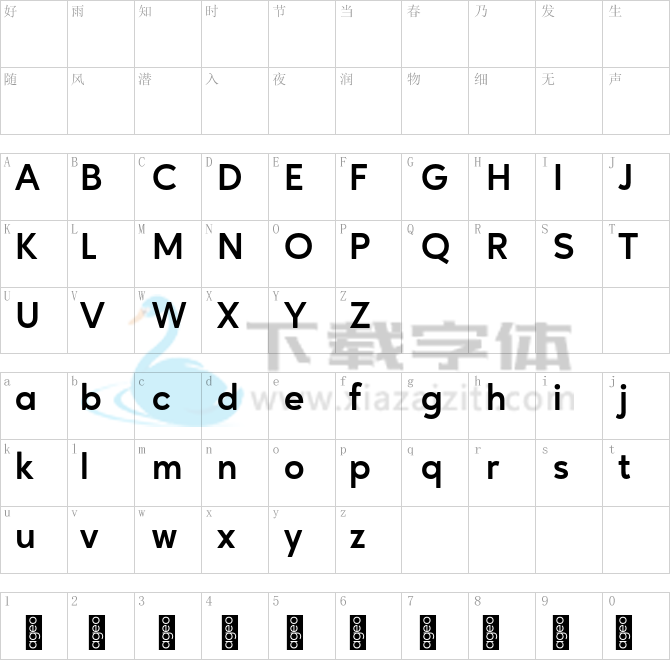
Ageo Personal Use.otf字体下载
Ageo Personal Use.otf字体下载,这款字体结构工整、笔画清晰,兼顾美观与易读性,适用于标题、正文、海报、包装、LOGO 等多种场景。字形优雅稳定,风格百搭耐看,适配日常排版与创意设计,让文字呈现更舒适、更具质感。Ageo Personal Use.otf字体下载一笔一画,皆是细节,以均衡的比例、流畅的线条打造舒适视觉体验,字形端正大气,风格简约现代。无论是商业设计、品牌宣传还是日常排版,都能轻松驾驭,让文字更有格调与力量。Ageo Personal Use.otf字体下载字体下载。